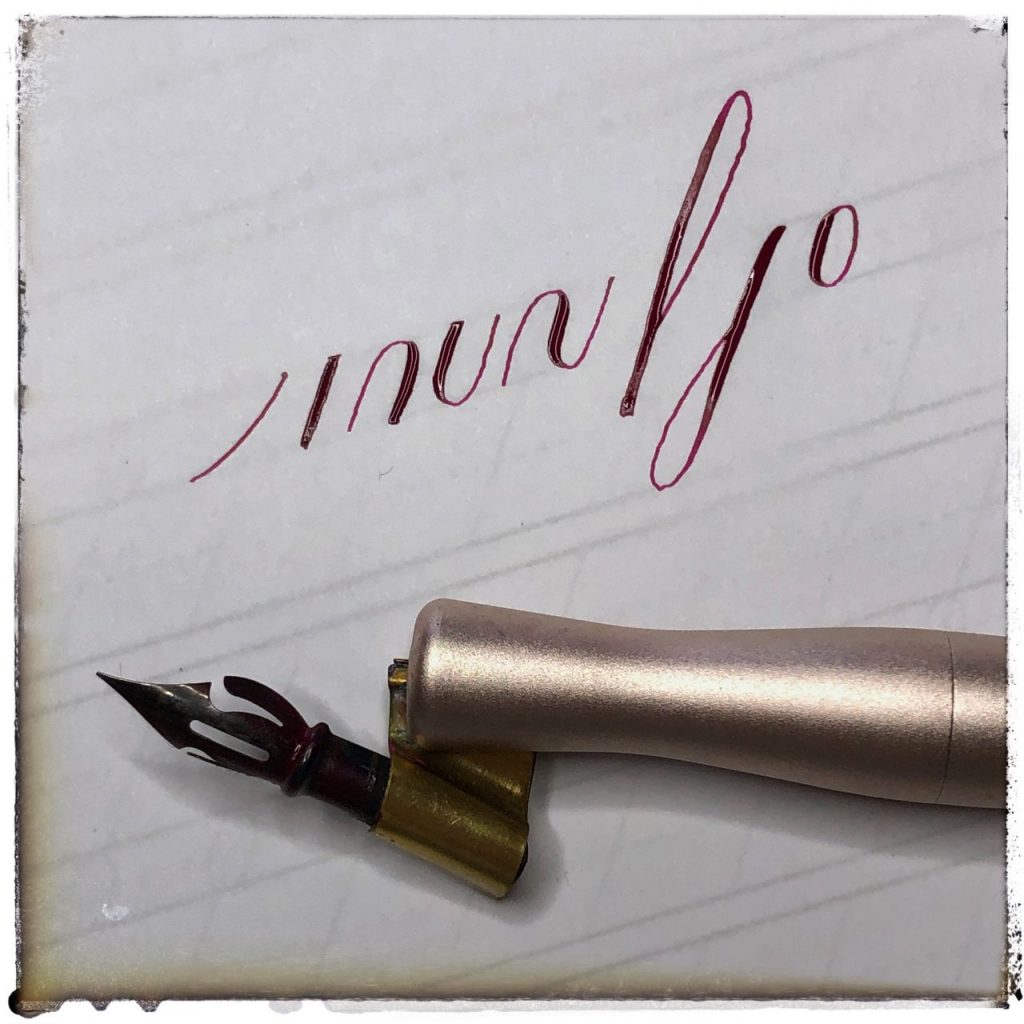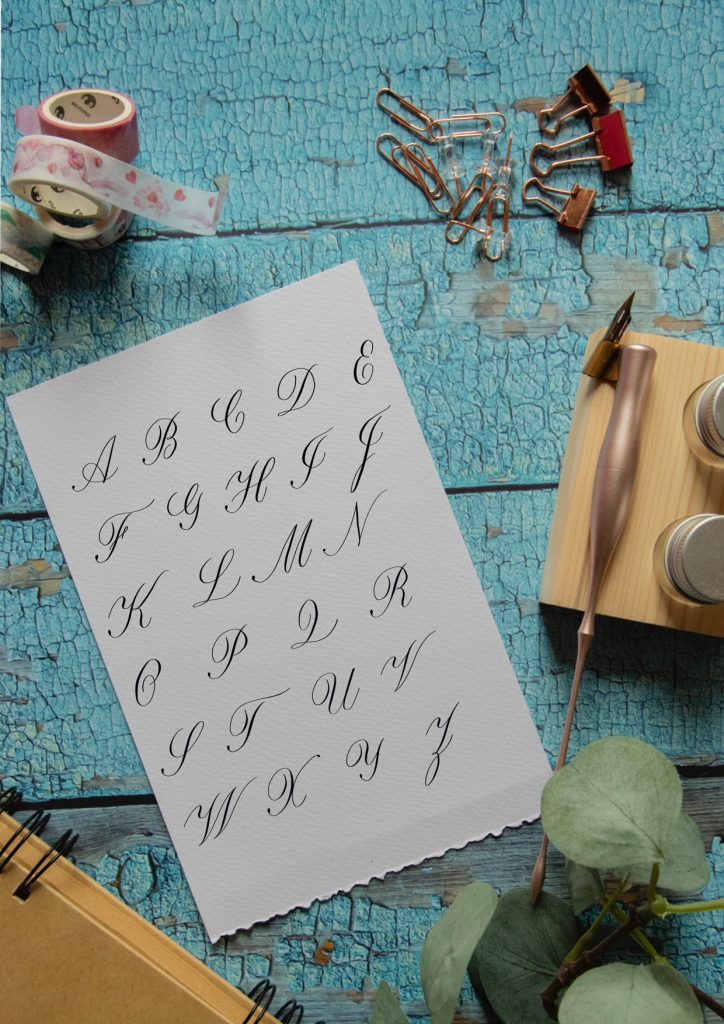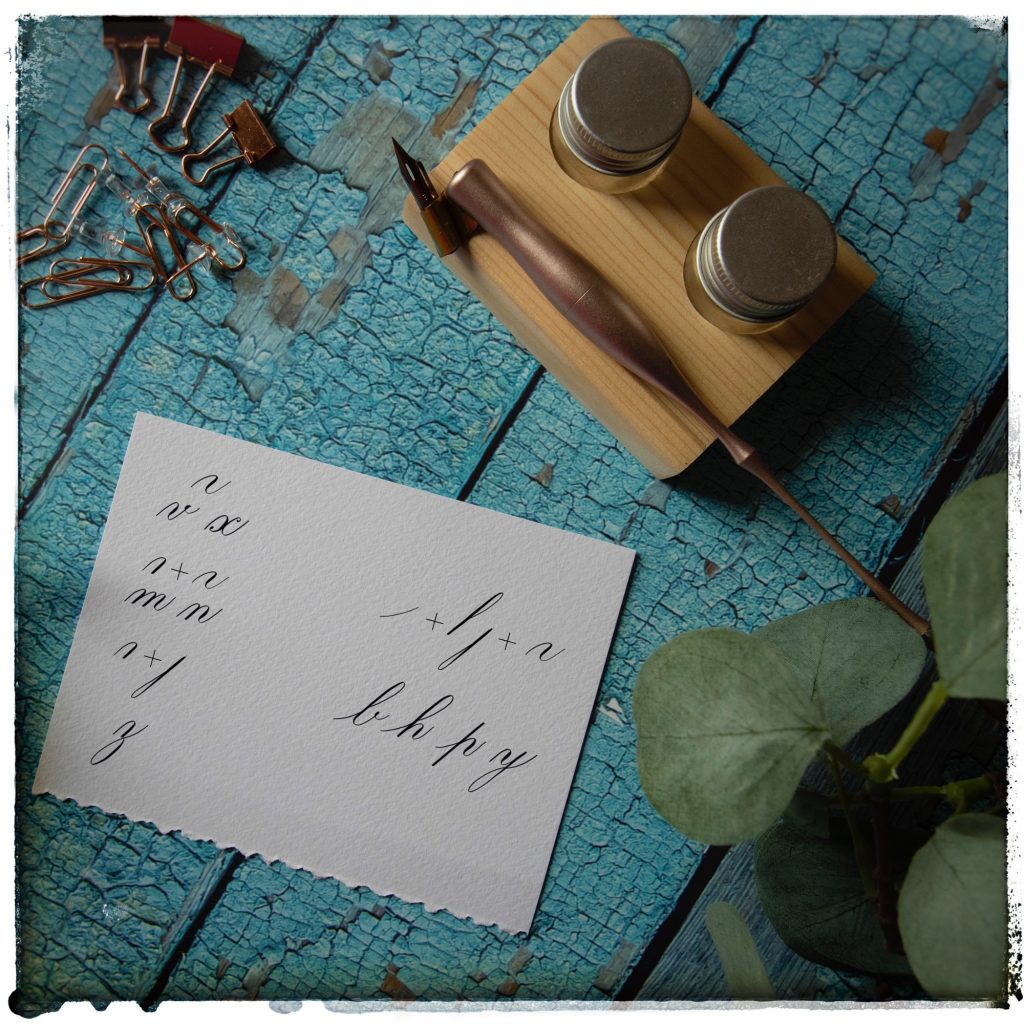
Copperplate kalligráfia
Ha rákeresel a kalligráfiára, akkor valószínű, hogy ezzel a típussal találkozol leggyakrabban, illetve ez az alapja a modern kalligráfiának is. Nézzük meg, hogy honnan származik és mik a jellemzői, hogyan tudod elsajátítani.
copperplate főkép
A Copperplate kalligráfia a legnépszerűbb, nagyon sokan tanítják és tanulják. Igazából bármelyik eszközt használhatod hozzá, mert szinte mindegyikkel el tudod érni a kívánt hatást. A legegyszerűbb talán az ecsetfilc. A legelegánsabb a mártogatós tollal lesz, azonban ha kezdő vagy inkább továbbra is az ecsetfilcet ajánlom hozzá.
A Copperplate rövid története
A Copperplate története egészen a 17. századig nyúlik vissza, és az angol folyóírásból fejlődött ki. Az angol folyóírás az üzleti ügyek intézéséhez elengedhetetlen volt akkoriban, ilyen betűtípussal születtek a szerződések és a könyvelés is ezzel a technikával készült. Aki sikeres akart lenni, annak meg kellett tanulnia szépen írni, mert csak így tudott érvényesülni az üzleti életben. Ehhez még valóban kihegyezett madártollat használtak az emberek, így valóban sokat kellett gyakorolni, hogy valaki igazán gyönyörűen, és olvashatóan tudja formálni a betűket. Az Angol Birodalom befolyásának köszönhetően pedig a legelterjedtebb írássá volt ebben az időszakban. Európában, Amerikában csak ezt használták az üzleti életben és a magán levelezéshez is.
Aztán a nyomtatás terjedésével, szerették volna ezeket a gyönyörű formákat is megőrizni, ehhez azonban az kellett, hogy valaki ezt felvésse egy réztáblára, amit azután már tudtak használni a nyomtatáshoz. 1931-ben használják először a Copperplate elnevezést, ami bizony erre a réztáblára utal, hiszen a copperplate réztáblát jelent. A népszerűsége azóta is töretlen, főleg, amióta megjelentek a fém tollszemek, amelyekkel ezt a jellegzetes vékony – vastag vonásokat sokkal könnyebb elsajátítani, mint a madártollal.
Hogyan is vágj bele a Copperplate tanulásába?
Ha már egy ideje olvasod a posztjaimat, akkor szerintem már tudod is a választ! 😊 Bizony, az alapvonásokkal! Hidd el, hogy sokkal gyorsabban tudsz majd haladni és fejlődni, ha jól begyakorlod ezeket. Ehhez segítségül, készítettem egy gyakorló lapot, amit ki tudsz nyomtatni, akár közvetlenül olyan papírra, amin tudsz gyakorolni, vagy akár átlátszóbb papír alá tudod tenni (erről itt írtam részletesebben).
Alapvonások
A kisbetűk anatómiája
Számomra a Copperplate nemcsak a vékony és vastag vonások váltakozása, hanem az oválisok játéka is. A legtöbb betű és vonás alapja az ovális, ami az 55 fokos dőlés szögön van rajta. Egy ovális magassága adja meg a betűk testének a magasságát, ezt szokás egy x-szel jelölni. Az alsó és felső hurkok magassága 1,5 vagy 2 ovális, én a 2 ovális magasságot használom leggyakrabban, számomra az a legkényelmesebb.
Kezdjük az ismerkedést azokkal a betűkkel melyeknek alapja tényleg az ovális:
Copperplate kisbetűk első csoport
A képen láthatod, hogy mely alapvonások kombinációjából állnak elő a betűk, ezért is fontos, hogy ezeket jól ismerd, mert látod az írás semmi más, mint ezek kombinációja.
A következő csoport, ahol az ovális baloldalát használjuk, azonban figyeld meg, hogy a kezdő része teljesen ráfekszik az alapvonal tetejére, és csak az alsó rész ovális, ezt hívhatjuk alsó vonásnak is emiatt.
Copperplate kisbetűk második csoport
Az utolsó előtti csoportban a hullámvonalat kombináljuk az előző csoportban használt vonás tükörképével, az az a felső vonással, illetve a hurkokkal.
Copperplate kisbetűk utolsó csoport
Most már ezeknek a képeknek a segítségével tudod gyakorolni a betűket, érdemes ezekben a csoportokban gondolkodnod, mert ahogy látod ugyanazokat a vonásokat használjuk a különböző csoportokban, így könnyebben tudod felépíteni végül a betűket.
Az Instagram profilomban találsz egy Copperplate mappát, ahol végig tudod nézni, hogyan kell írni a kisbetűket.
A nagybetűk anatómiája
A nagybetűknek is vannak alapvonásai, amiből felépül, szám szerint 15 darab, talán ebből is láthatod, hogy ezeket nehéz egy sémára felhúzni, így inkább bemutatom őket egyben, és fedezd fel, hogy melyek lehetnek ezek a sémák. Itt még inkább érvényesül az, hogy az oválisokra figyelj, mert minden egyes vonása a nagybetűknek ezekre az oválisokra épül. Azért érdemes ezekre már most odafigyelni, mert ha szeretnél tovább menni a díszítésre, angolul a flourshingra, akkor ott is ezekkel a formákkal fogsz játszani. Számomra a legtökéletesebb művésze a flourshing témának Younghae, akitől volt is lehetőségem tanulni. A Tőle tanultakat használtam kezdőképhez is. 😊
Copperplate nagybetűk